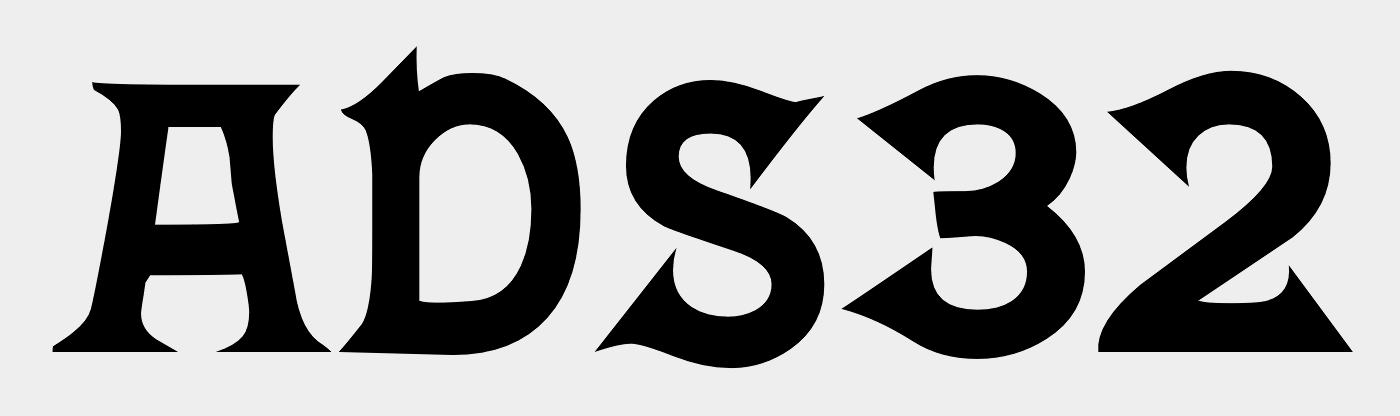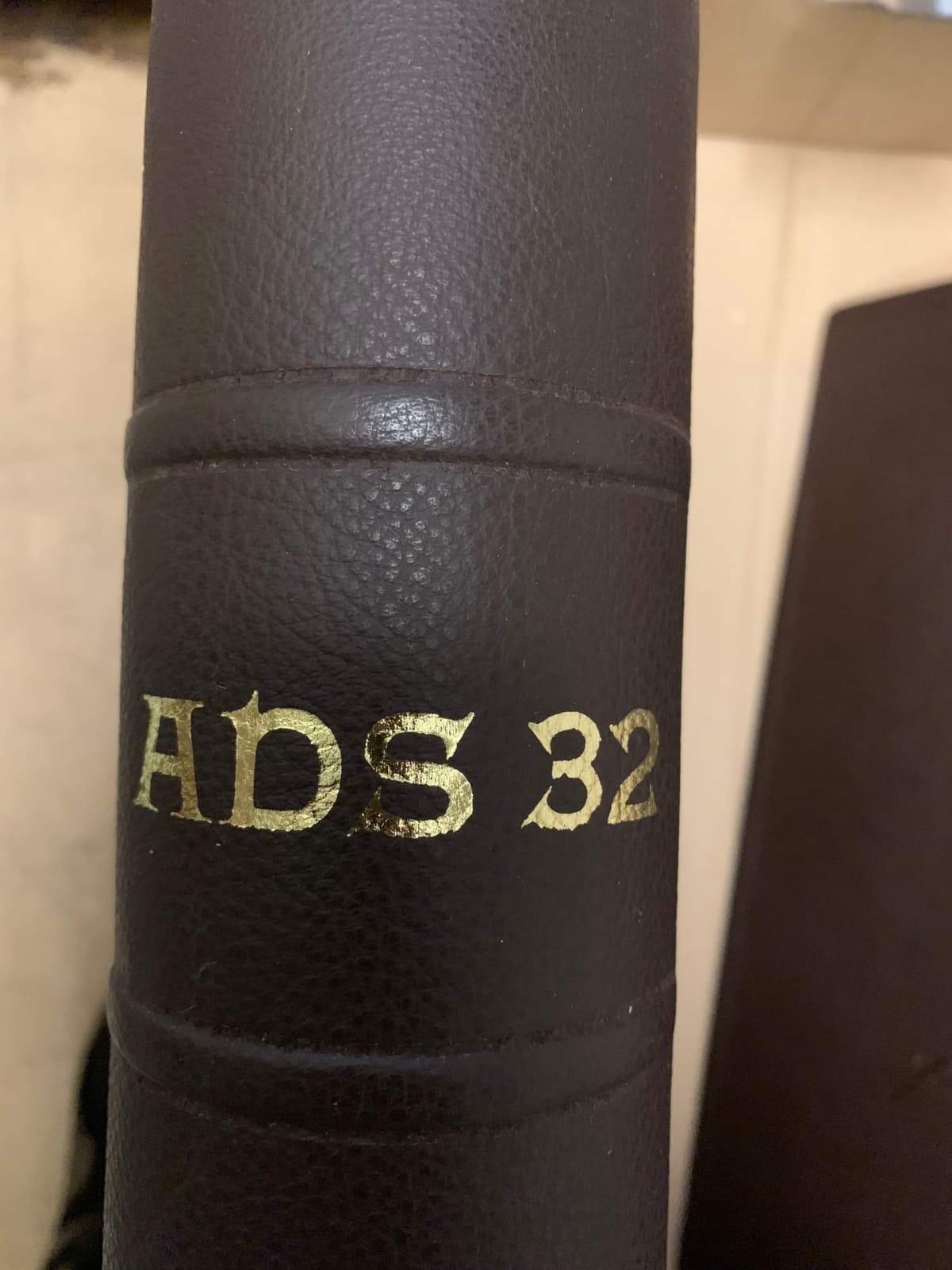
Prägeschriftart gesucht
Hallo, eine Kollegin hat mich um Hilfe gebeten. Sie sucht die abgebildete Schrift (wahrscheinlich soll sie einen Titel in dieser Schrift prägen, also eine Reihe fortführen). Wie ihr seht, handelt es sich um eine Prägung auf einen Buchrücken, keinen Druck. Ich glaube aber nicht, dass das eine spezielle Prägeschrift ist/war. Bisher bin ich leider nicht weitergekommen.
Wer kann helfen?
Wäre doch schon mal sehr nahe dran …
Die Kleinbuchstaben-Belegung passt noch besser. Schade, dass bei den Scriptorium-Fonts die historische Originalquelle nicht angegeben ist. Vom Stil her gut möglich, dass tatsächlich Prägebuchstaben Pate standen. So richtig massentexttauglich ist das ja nicht.
Aber man könnte von dem obigen Font neue Messingvorlagen machen, wenn das wirklich das Ziel ist. Die Originalschrift noch einmal in Messing zu finden, ist eigentlich utopisch. Da nützt auch der Originalname wenig.
Warum?
Weil sich für solche Termotransferprägungen auch ganz normale Bleilettern eignen, und hierfür eben auch Kasetten mit Bleilettern zu den Buchbinder Prägepressen geliefert werden.
Sieht sehr gut aus; die obere Serifen-Form beim D ist in der Prägung etwas runder, aber so viele Schriften mit diesen Formen gibts ja nicht …
Üblich sind in der Buchbinderei eher "Toastbrot-"Schriften, die zu vielem passen und okay aussehen. Daher findet man meistens eine Diethelm für die Serifen und eine Helvetica für die Serifenlosen, als Altbestand oft als Bleisatzlettern. Die Qualität der heute gegossenen Schriften für Buchbinder lässt extrem zu wünschen übrig, oft ist die Kegelhöhe nicht einheitlich oder Lettern in größeren Schriftgraden zerbröseln. Wobei Bleisatz-Lettern aufgrund der Kegelhöhe ja nur für den Prägnant zu gebrauchen sind. Für Prägepressen gibt es wieder spezielle Lettern, meist aus Messing, die in der Höhe Klischees entsprechen und aufmontiert werden müssen.